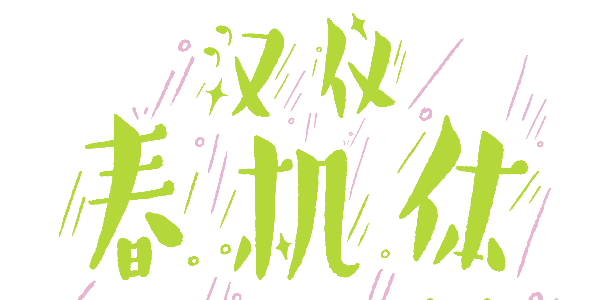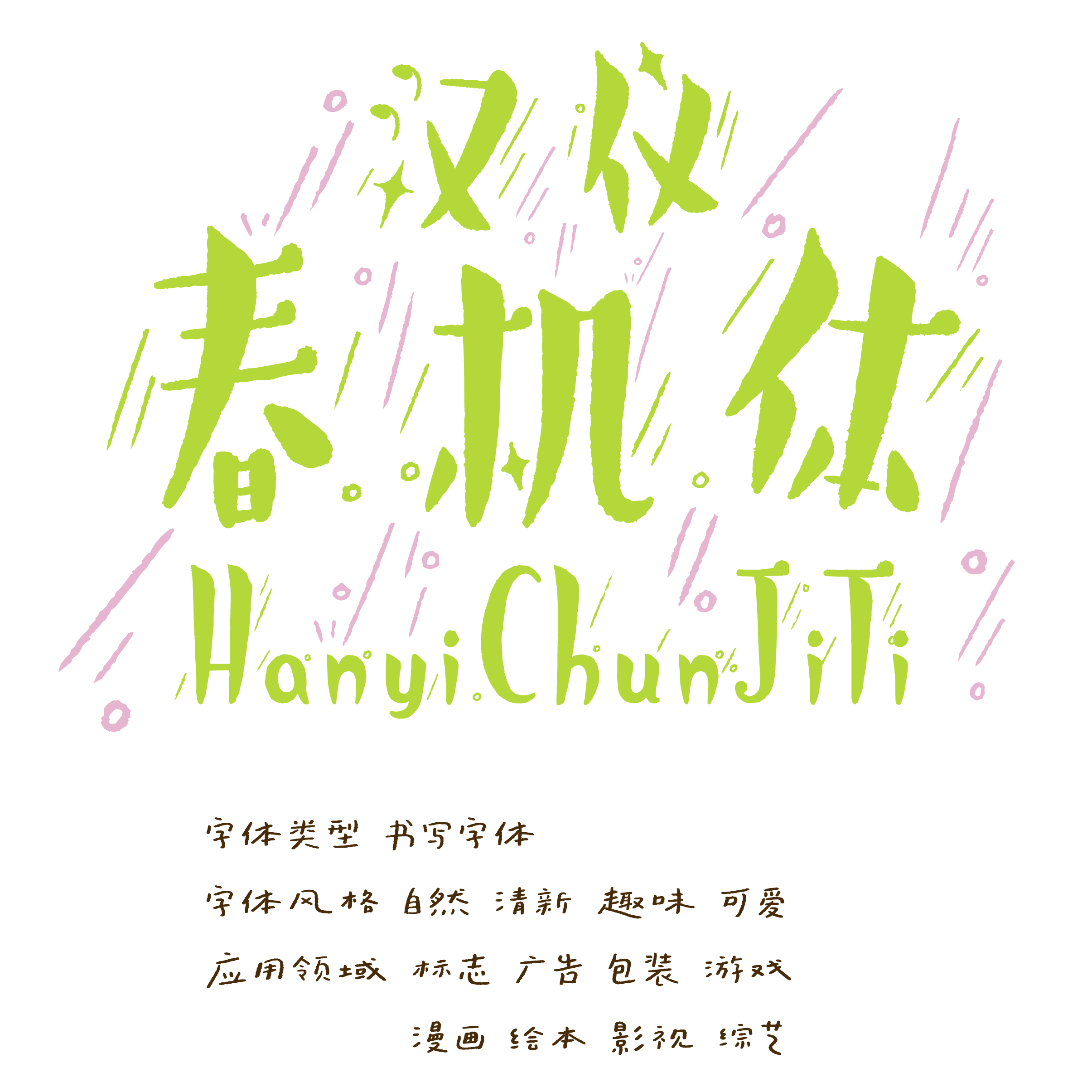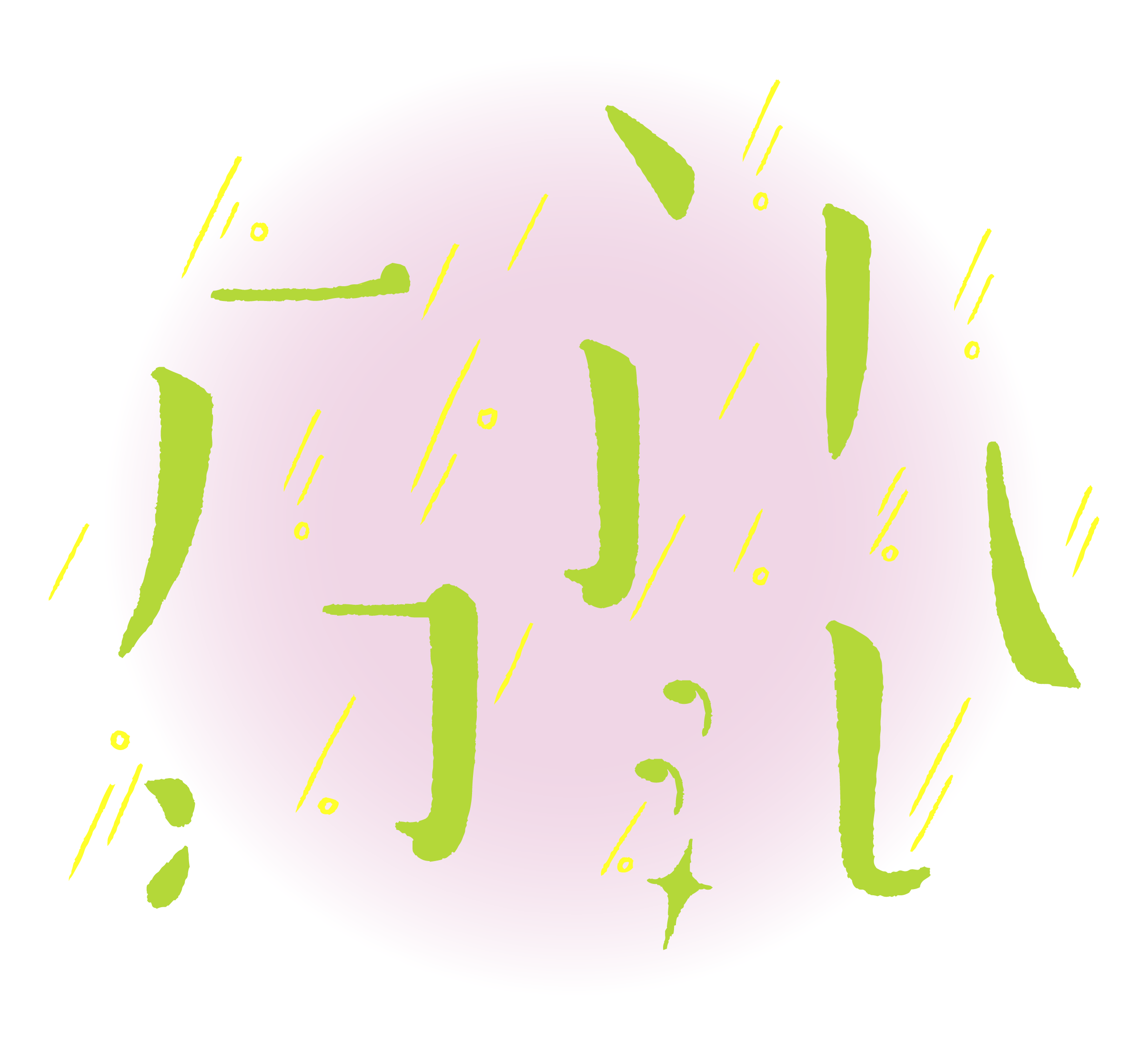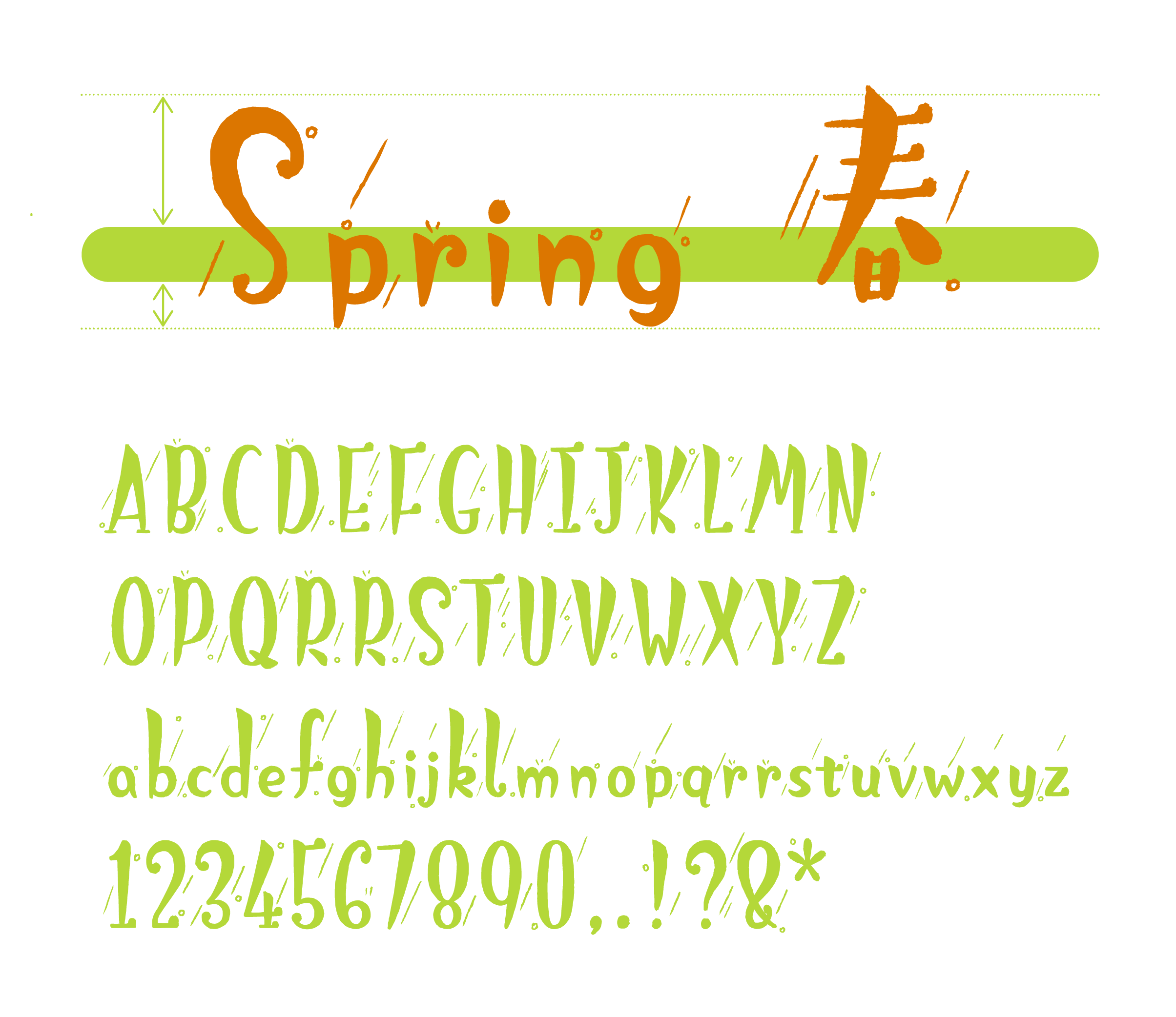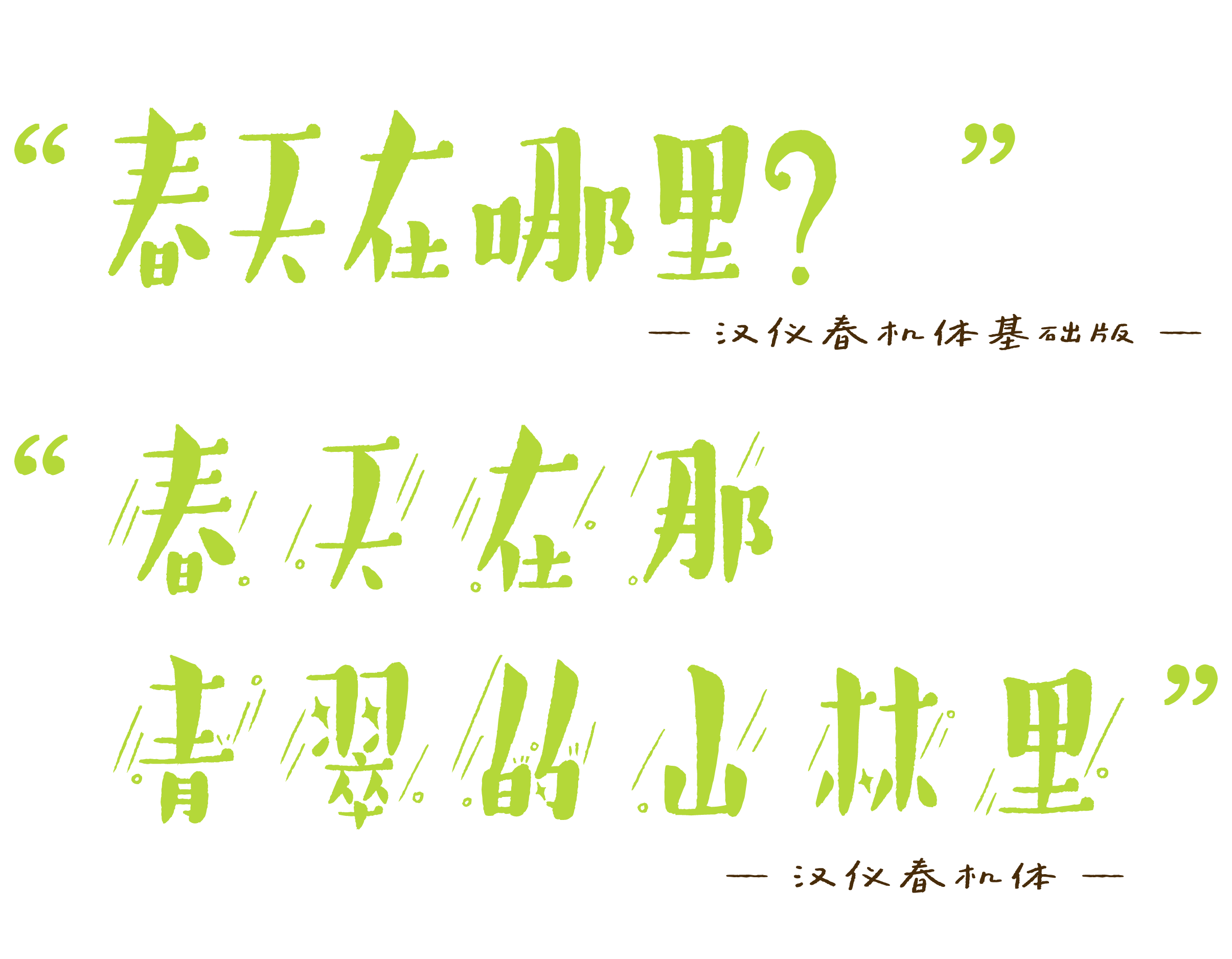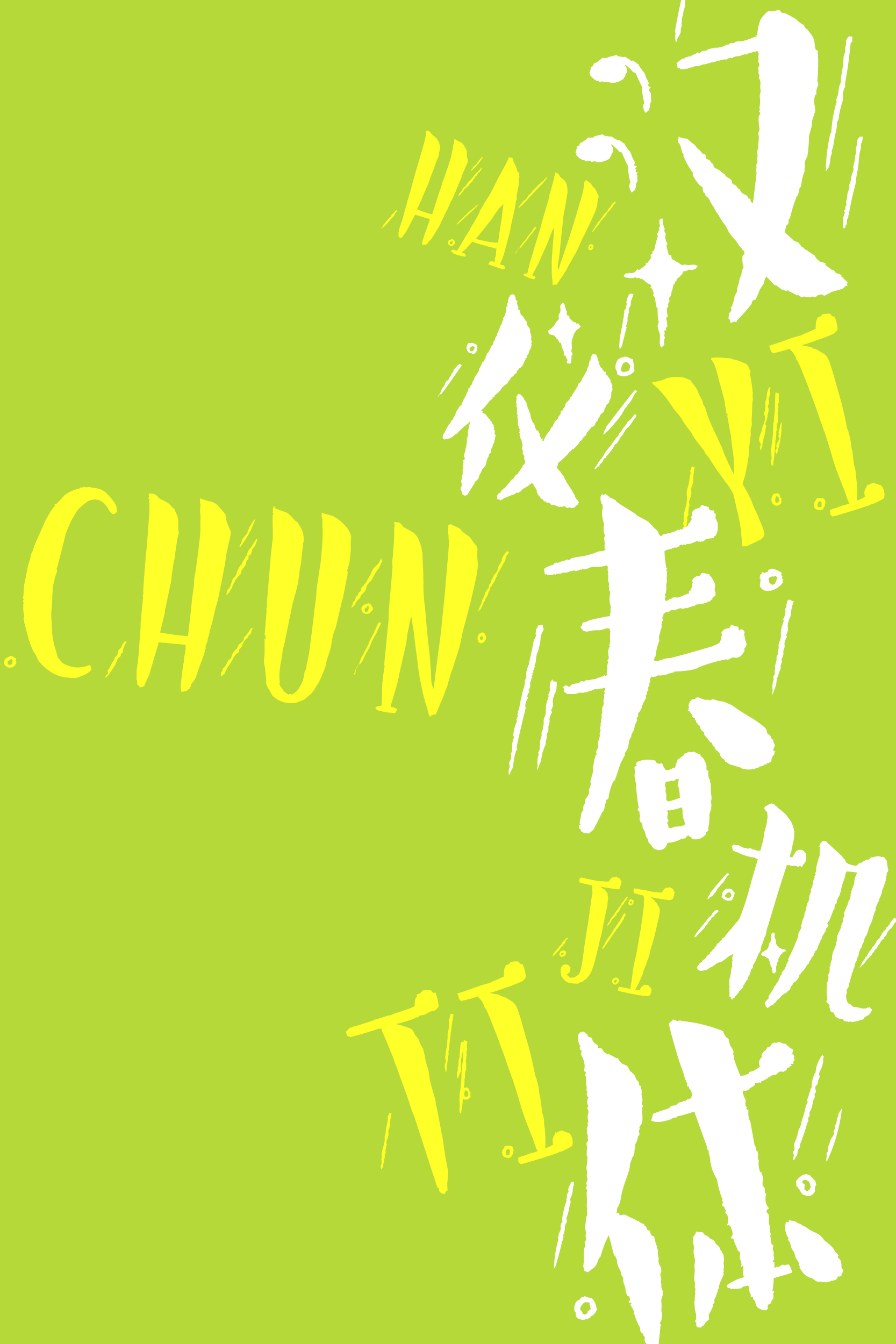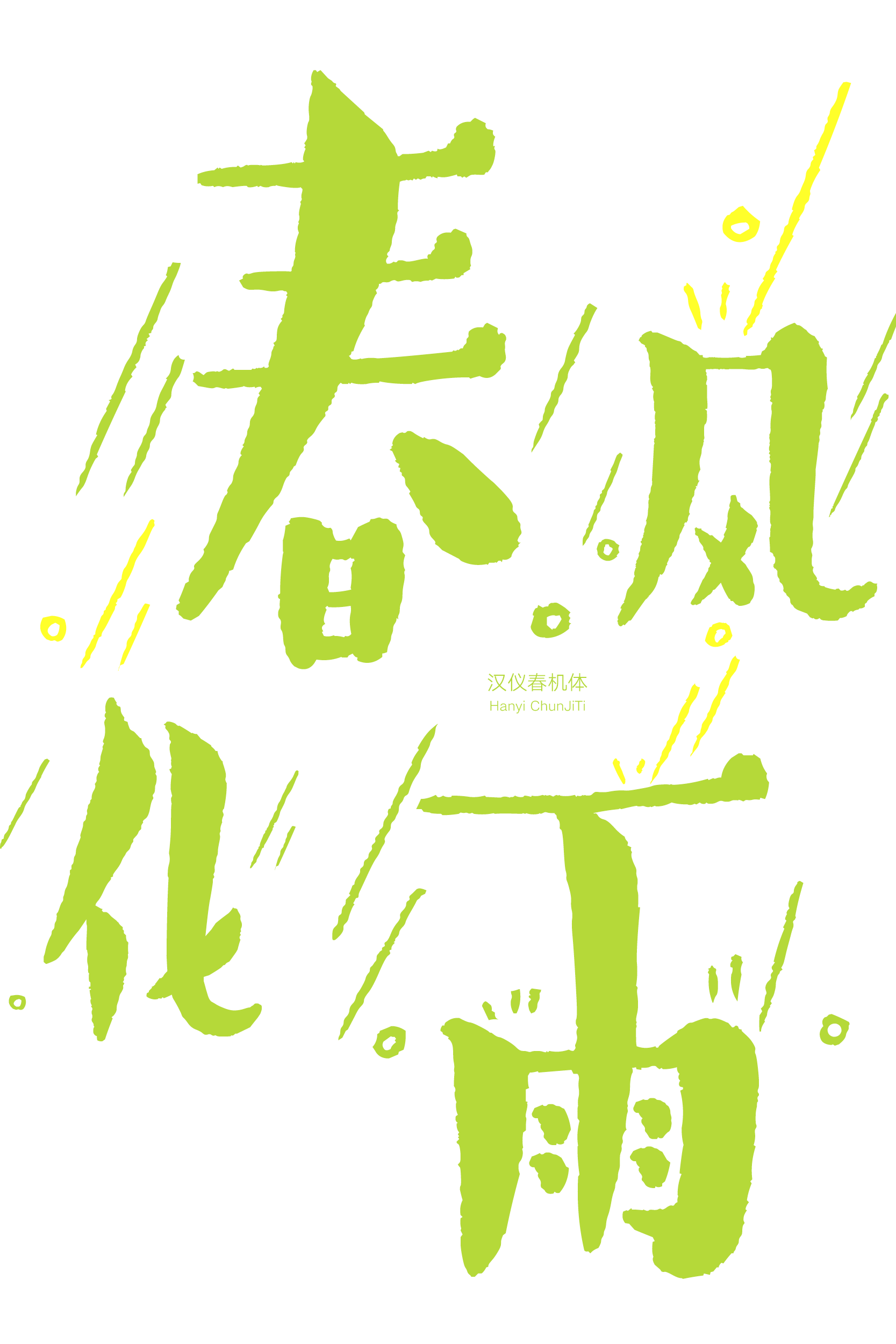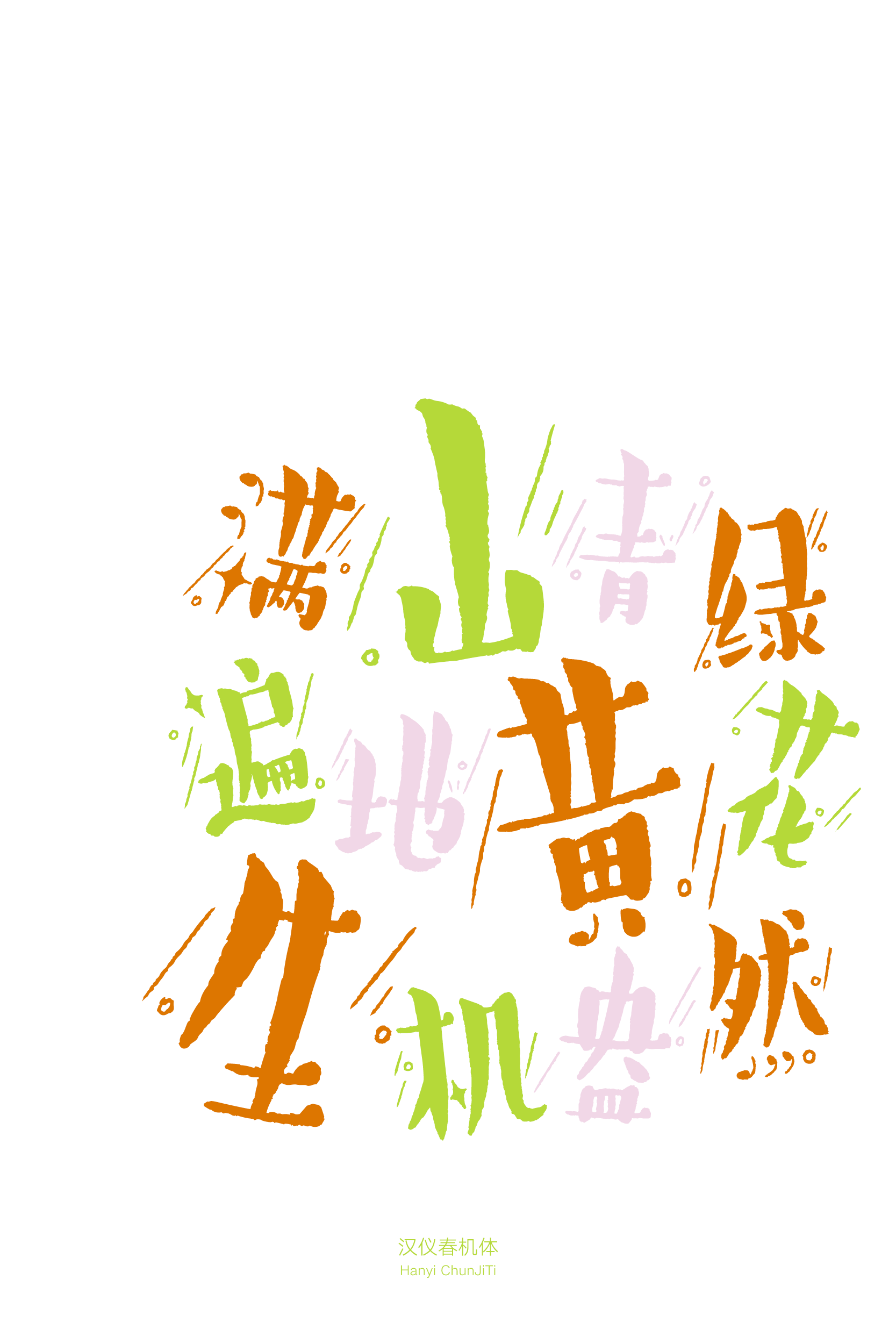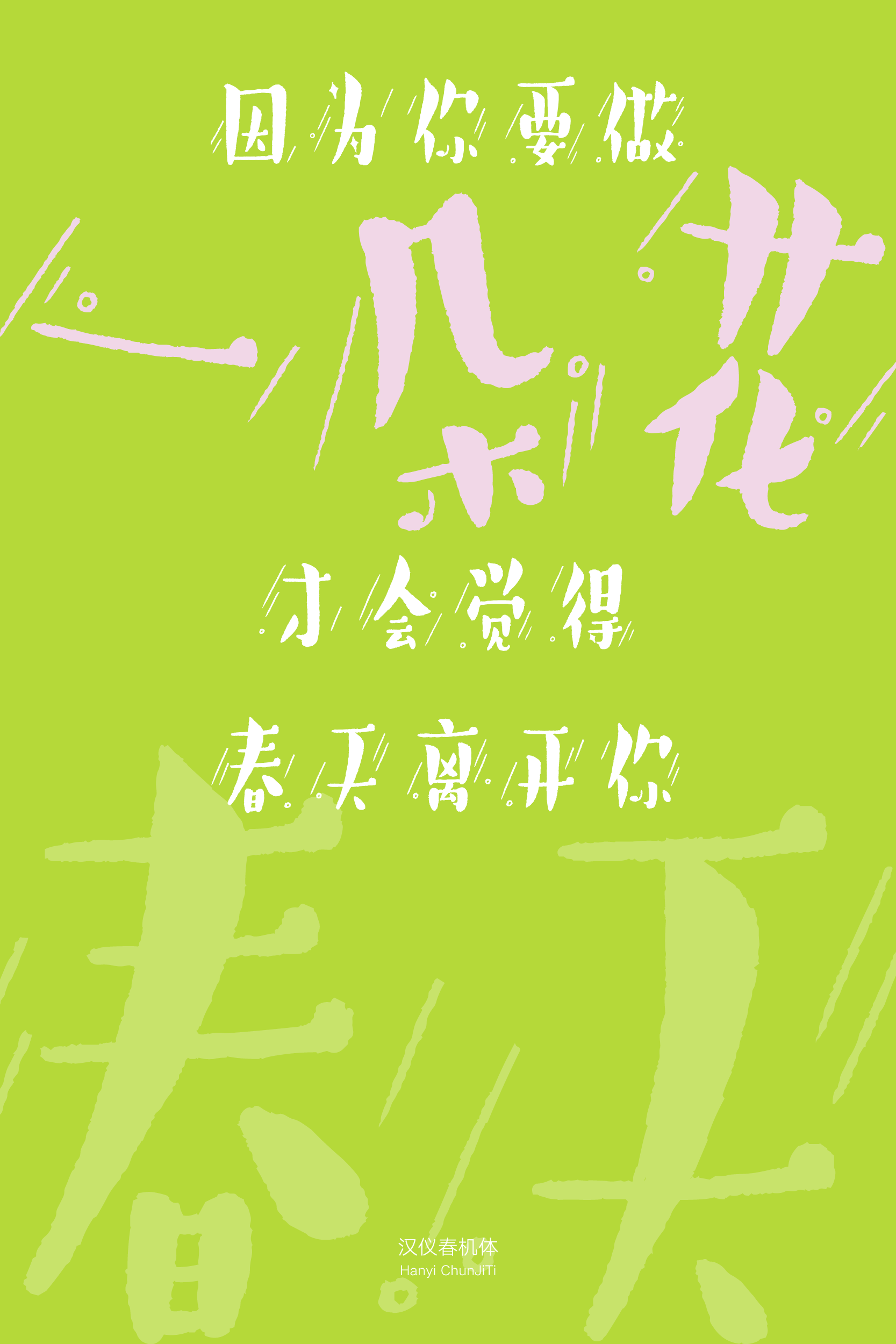
汉仪春机体
汉仪春机体,文字如同草木萌芽,沐浴在春雨中,昂扬向上,挺拔生长。漫画般夸张的字形瘦长而重心极低,笔画饱满,点缀以星星、逗号的装饰笔画,搭配细细的斜线和错落的圆圈,春机盎然,万物生长。这款手写字体带来生动的画面感,赋予文字鲜活的生命力,适合作为标题或装饰字体应用于漫画绘本、综艺影视、广告包装等不同场景,无论静态或动态都有着独特的趣味。
汉仪春机体的基础字形瘦长而重心极低,微微倾斜,如同草木萌芽向上生长。
笔画饱满,轻松生动。
以星星、逗号的装饰元素替换部分笔画,使字体的“表情”更为生动活泼。
细细的斜线和错落的圆圈,像是春雨在和煦的春风里飘落。
汉仪春机体的西文以极小的x字高、放大的上伸部和缩小的下伸部对应中文上大下小的夸张造型,点缀春雨般的装饰元素,中西文视觉语言一致。
同系列的汉仪春机体基础版,省略了装饰元素,只保留夸张的基础字形,两款字体可搭配应用于不同的使用场景。